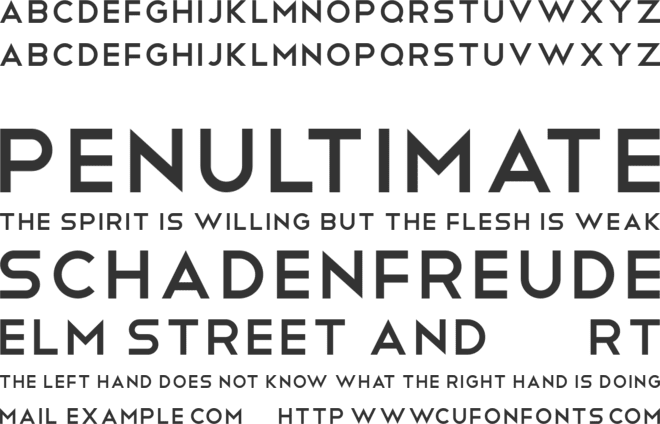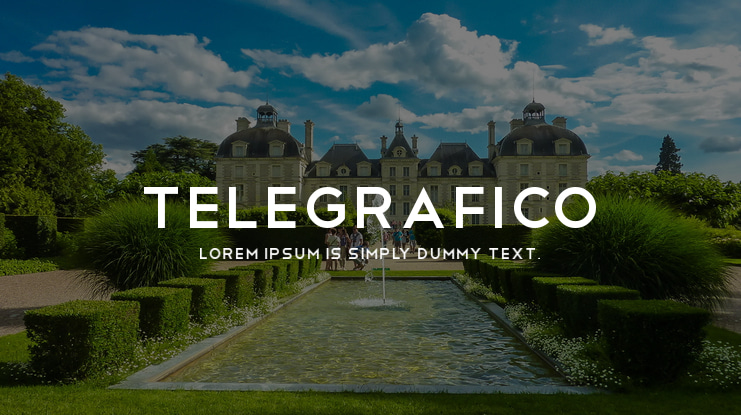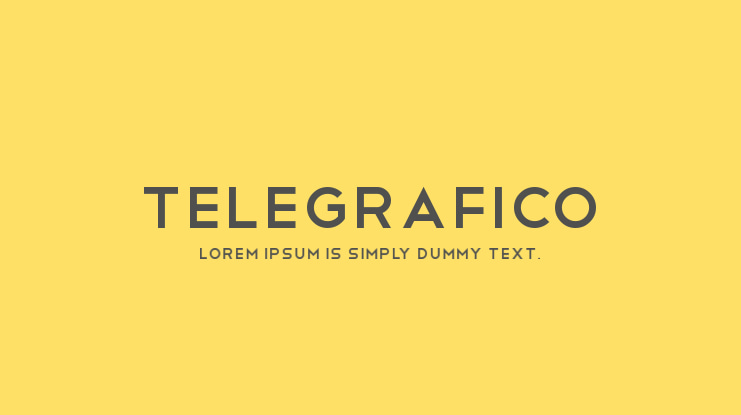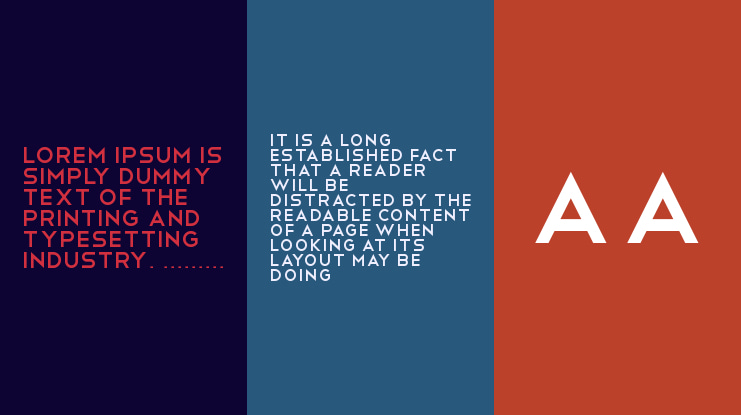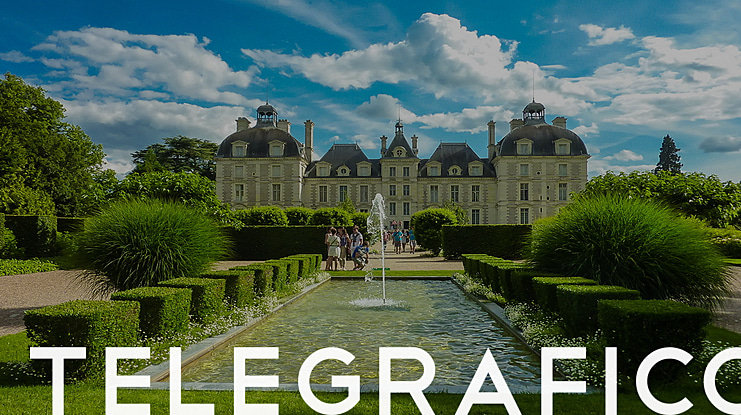
Telegrafico Font
non posso certo rivendicare la creazione delle forme di questo font, cosa che peraltro credo sia molto discussa, in genere, fra i fontmaker... rivendico perÚ "questa" trasposizione digitale del "tipo" (arcinoto a tutti gli italiani, almeno) cui mi sono ispirato.